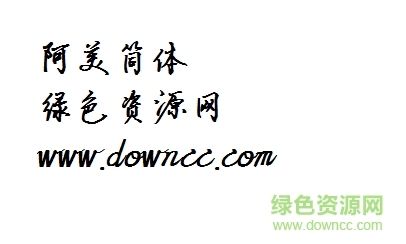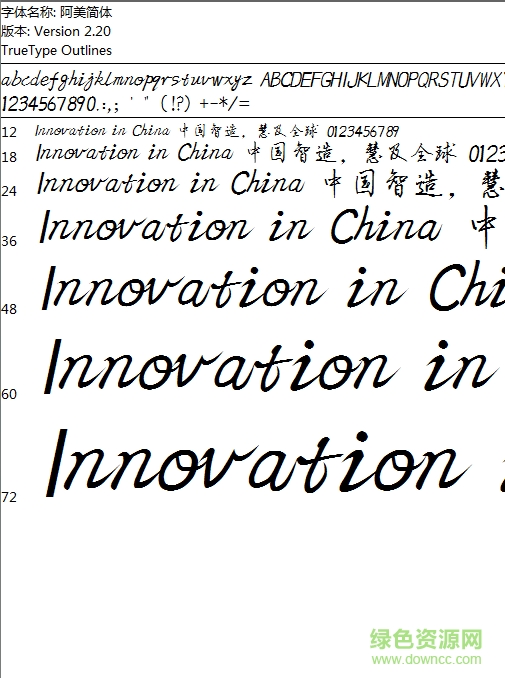
阿美簡體字體
阿美簡體是一款好看的中文字體,字體筆畫形如流水,非常連貫,頗有一種草書的感覺,整體效果優(yōu)美時尚,喜歡的朋友歡迎下載使用,綠色資源網(wǎng)更多好看免費字體下載!
一款簡潔唯美的鋼筆行書字體??梢詮V泛應(yīng)用于名片設(shè)計、新聞媒體、宣傳海報、ppt、影視制作以及內(nèi)容用字等領(lǐng)域。